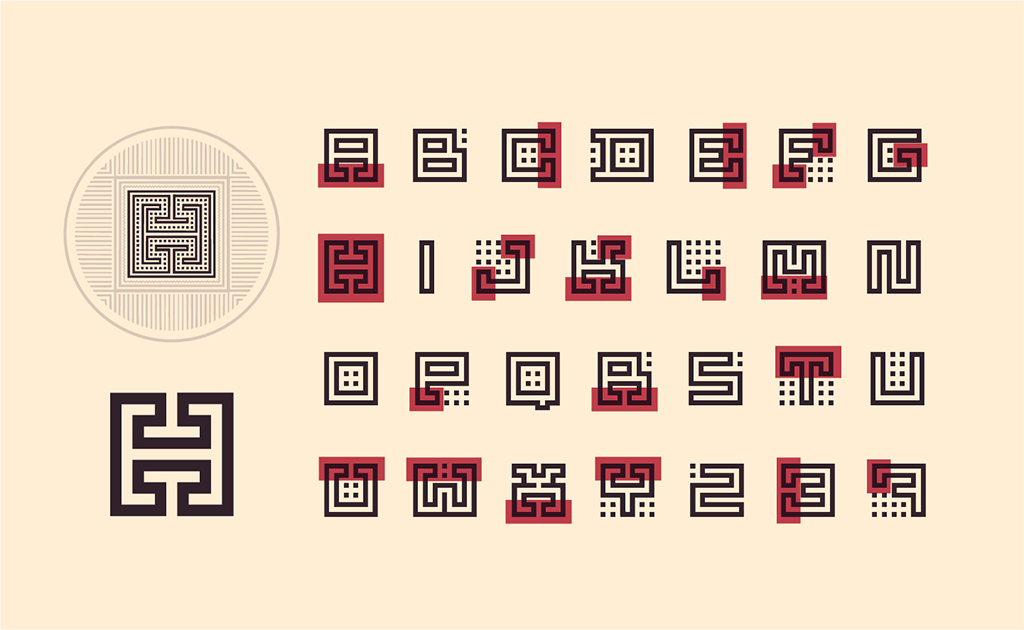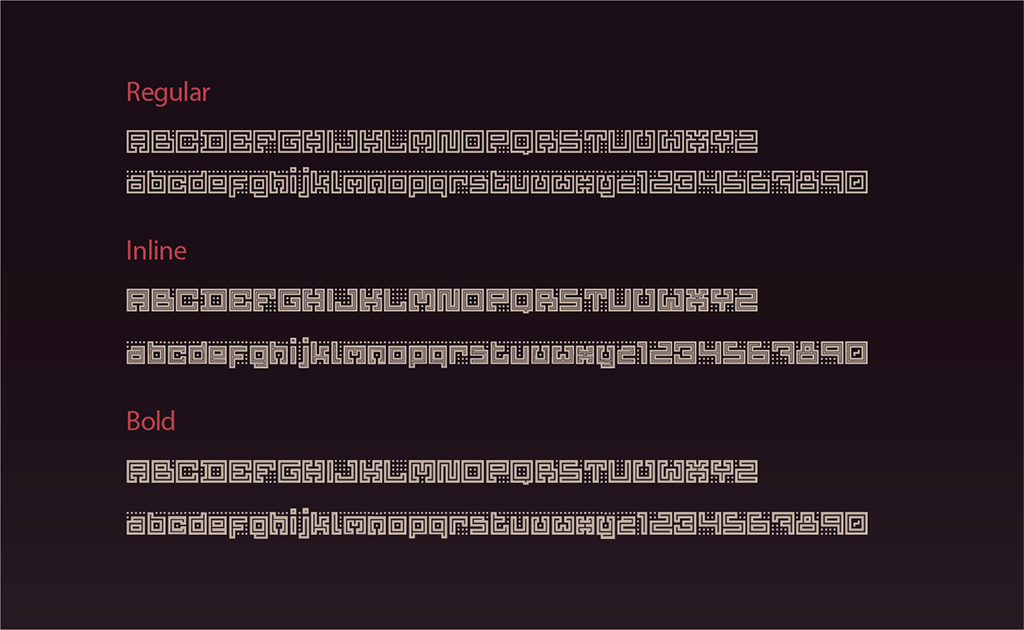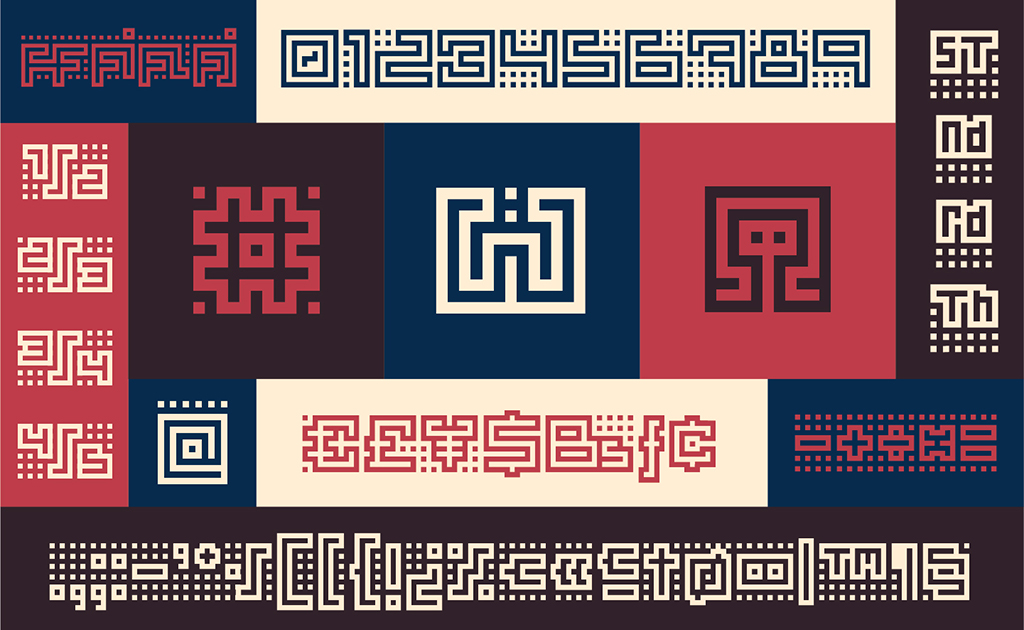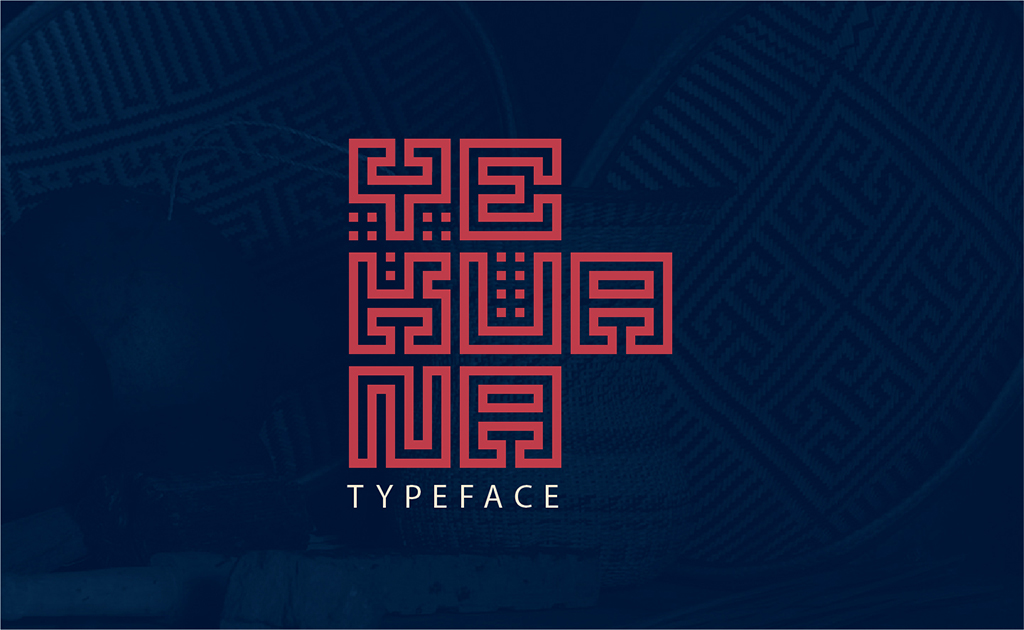
Tipografía Yekuana es una fuente de visualización diseñada para titulares y frases breves de gran impacto. Su construcción parte del estudio de signos geométricos ancestrales vinculados a la cultura material de una de las tribus aborígenes más emblemáticas de Venezuela.
La familia cuenta con dos pesos e integra alternativas estilísticas, fracciones, ordinales y ligaduras. La combinación por capas y el uso de colores contrastados amplían el repertorio visual y permiten resolver piezas editoriales con una voz gráfica potente y contemporánea.
Desarrollada por Neo Type Foundry, Yekuana logra una síntesis entre memoria cultural y desempeño tipográfico para formatos de alta visibilidad. El proyecto destaca por traducir referencias simbólicas en una herramienta funcional para diseño editorial e identidad visual.
País: Venezuela
Estudio / proyecto: Neo Type Foundry